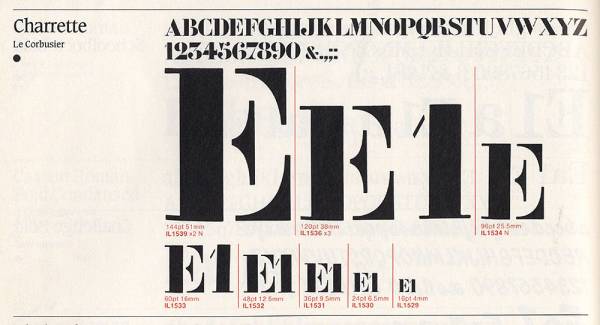
Schrift gesucht (Le Corbusier)
ich suche mal wieder eine Schrift. :)
Muss nicht genau diese sein, aber eine oder mehrere ähnliche Möglichkeiten...
Benutzt von Le Corbusier auf einem Architektur-Grundriss.
Eventuell hilft dir auch das etwas weiter:
quot21x16.gifCharrette is a stencil typeface inspired by the lettering on Swiss architect Le Corbusier's drawings. It used to be available as a Letraset rubdown dry transfer (upper case only). Today there are at least two nice digital versions: Modular Stencil and Le Corbusier.
Ja, zur Not geht auch Vtg Stencil Germany No.1.
Aber das S der Franzosen ist schon etwas eigenwillig. Der obere Schwung ist merklich zurückgenommen. Zudem gab es zwei franz. Hersteller dieser Schablonen deren Designs sich gut an Q und J unterscheiden lassen - kleinere Unterschiede gibt zudem in den Designgrößen.
Tja, Picasse & Co. haben die Dinger auch genutzt - weil die Schablonen einfach verbreitet und ganz gewöhnlich waren.
Irgendwann mach ich mal die France No.1.